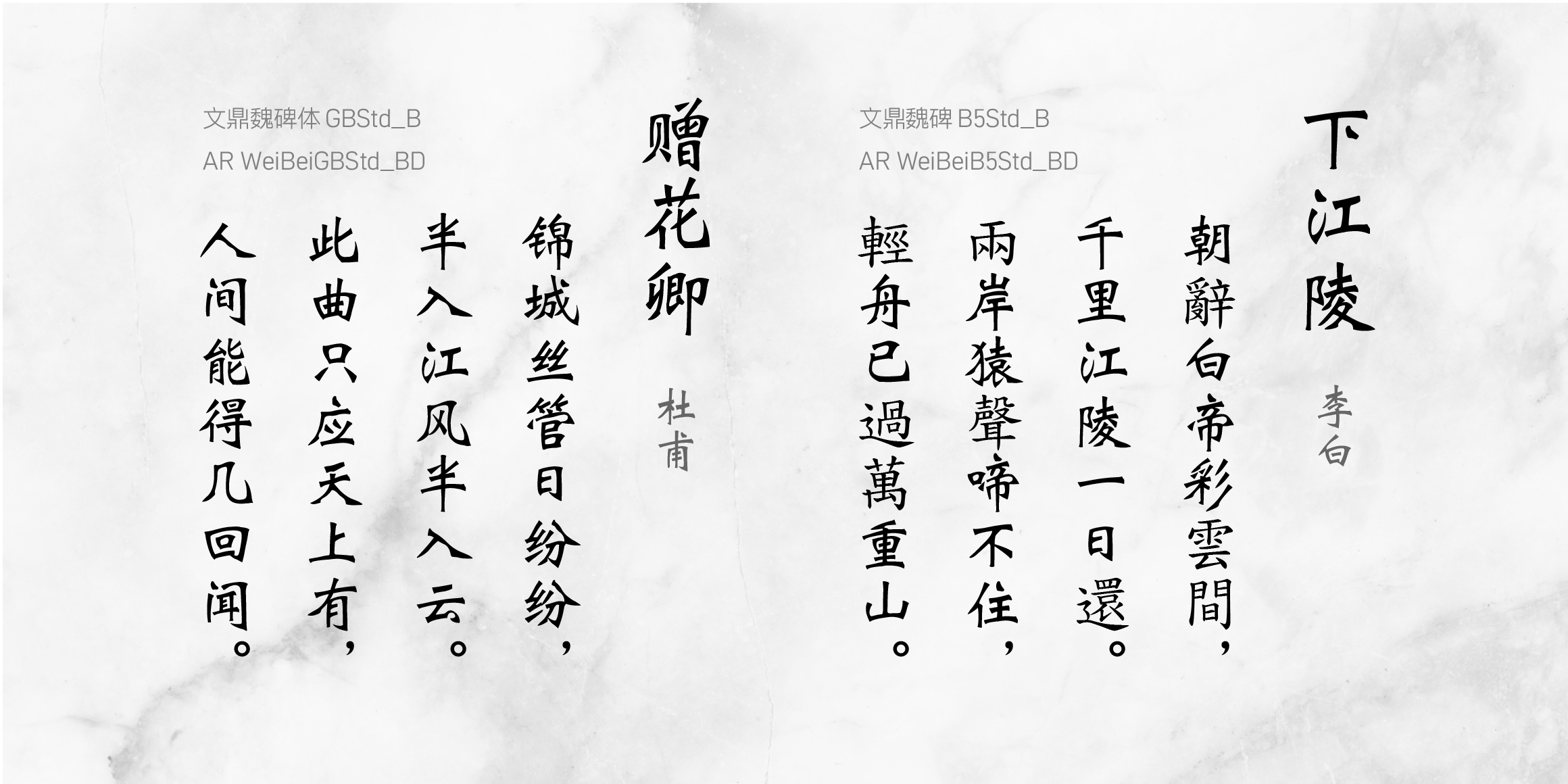
AR WeibeiGB
07 Bold
WeibeiGB는 단단함 속에서도 부드러운 인상을 주기 위해 탁본의 특징을 가져온 폰트이다.고대 중국 북부 왕조의 탁본에서 영감을 받아 제작되었다.폰트명 뒤에 붙은 GB라는 표기는 간체의 문자코드를 뜻한다. 간체란 중국에서 주로 사용하며 필획을 줄이고 자형을 간단하게 만든 한자다. 대만, 홍콩, 마카오 등에서 사용하는 번체(B5)와는 달라 잘못 적용할 경우 글립이 제대로 표기되지 않거나 다른 글립으로 표기되는 문제가 발생할 수 있다.